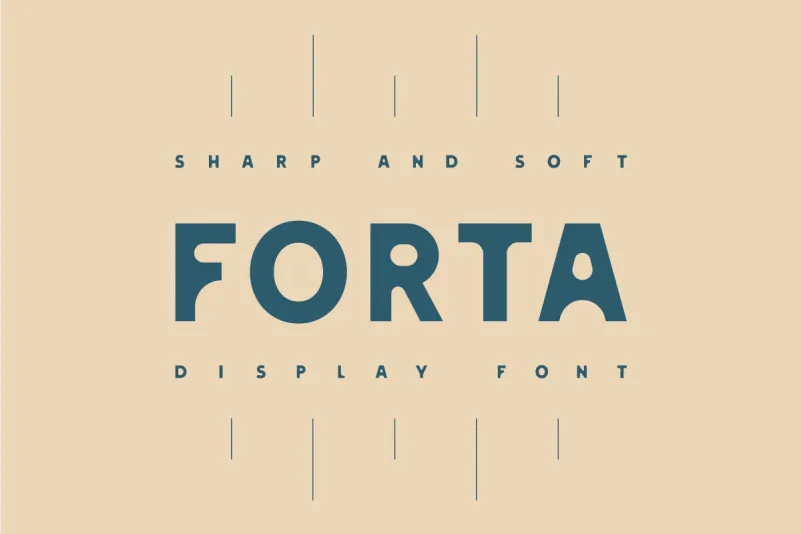
Forta Display Font é uma elegante tipografia sans-serif com detalhes de abraço que captura as roupas vintage dos anos 70. Inspirada na letra bela encontrada em etiquetas antigas, esta fonte foi projetada por Andrzej Wróż, um designer gráfico e diretor artístico de Poznań, Polônia. Forta Display é uma fonte ‘all caps’, perfeita para headlines, frases curtas, logotipos e cartazes. Ela combina linhas agudas com curvas suaves em formas únicas e visualmente atraentes. Forta Display contém mais de 190 caracteres gerais e suporta mais de vinte idiomas. Suas características incluem abraços delicados que dão um toque romântico à tipografia, combinando com o estilo clean dos caracteres sem serif em um equilíbrio harmônico. Este projeto de fonte é perfeito para aqueles buscando uma combinação única e sofisticada de design vintage e moderno. Através da Forta Display, você pode incorporar elementos de design antigos em projetos atuais, criando um visual que é tanto nostálgico quanto contemporâneo.